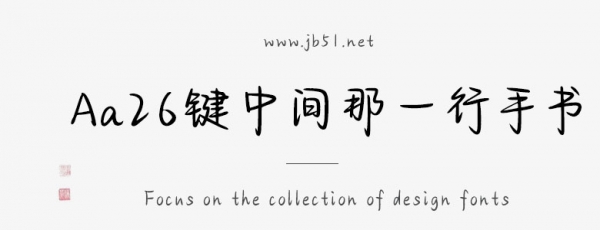
Aa26鍵中間那一行手書(shū),字體筆觸略細(xì),書(shū)寫流暢,略顯俏皮可愛(ài),具有很好的視覺(jué)感,適合應(yīng)用于藝術(shù)設(shè)計(jì)、平面宣傳設(shè)計(jì)、網(wǎng)頁(yè)設(shè)計(jì),書(shū)法字帖等領(lǐng)域。有需要的朋友快來(lái)本站下載使用吧。